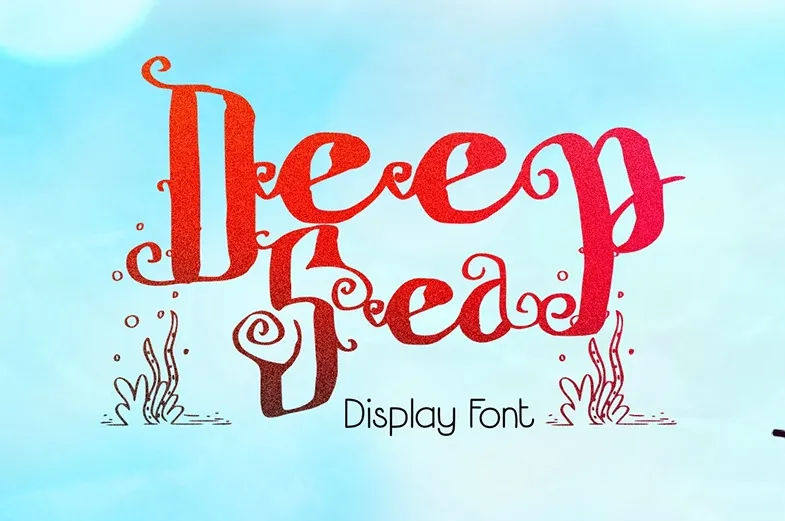
Aqui está uma versão dos dois parágrafos curtos para a descrição do download da font ‘Deep Sea Typeface’, mantendo os requisitos: “O projeto da nova e única fonte que apresento é nada mais, nada menos, que Deep Sea Typeface. Ela é feita 100% à mão e criada pelo talentoso designer Slamet Bagus Panuntun. Essa font é uma criação artística, com um tema focado na natureza marinha e seus habitantes. Ideal para qualquer projeto, desde logotipos e sinalização, até camisetas e embalagens. Deep Sea Typeface representa o melhor de sua categoria.” Esta descrição fornece uma visão concisa e atraente do produto sem se alongar demais sobre características específicas da fonte. Ela mantém um tom informativo e convidativo para um público que busca recursos gráficos, destacando os atributos mais relevantes como sua artefulness, versatilidade de uso e tema único.